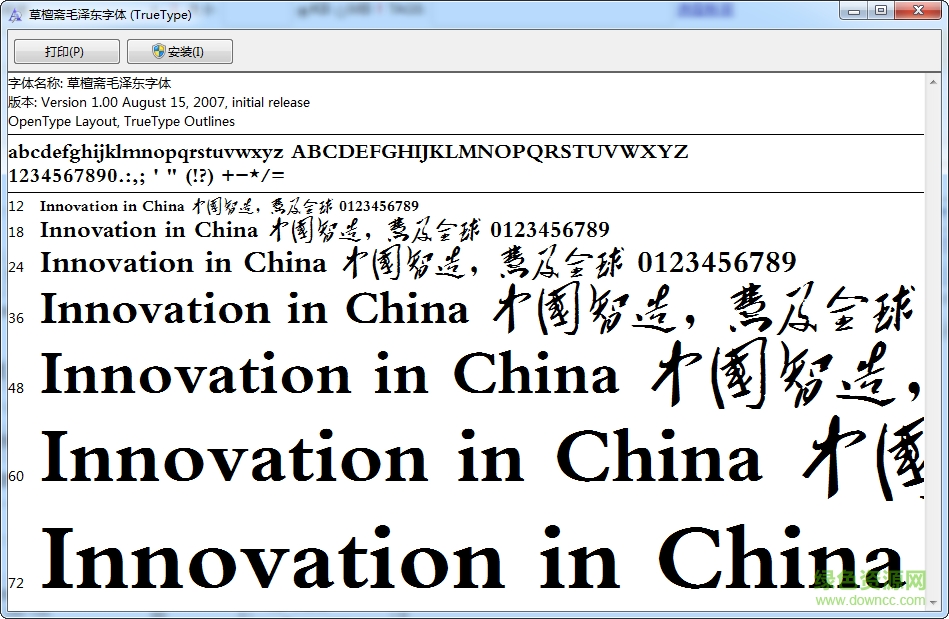
毛體字體是一款以偉大無產(chǎn)階級革命家毛澤東同志的手寫字體研發(fā)而來,字形有氣勢、有力度、有神韻,生動活潑,柔韌雄強,彰顯了中華民族精神,有喜歡的朋友趕緊來綠色資源網(wǎng)下載使用!
毛體字體是以高清晰《毛澤東書古詩詞手跡》,《題詞系列手跡》為基礎(chǔ)開發(fā)的,集手稿字一萬兩千余個,字體整體風格統(tǒng)一。集眾美于一體,有豐富的美學內(nèi)涵,達到很高的藝術(shù)境界。